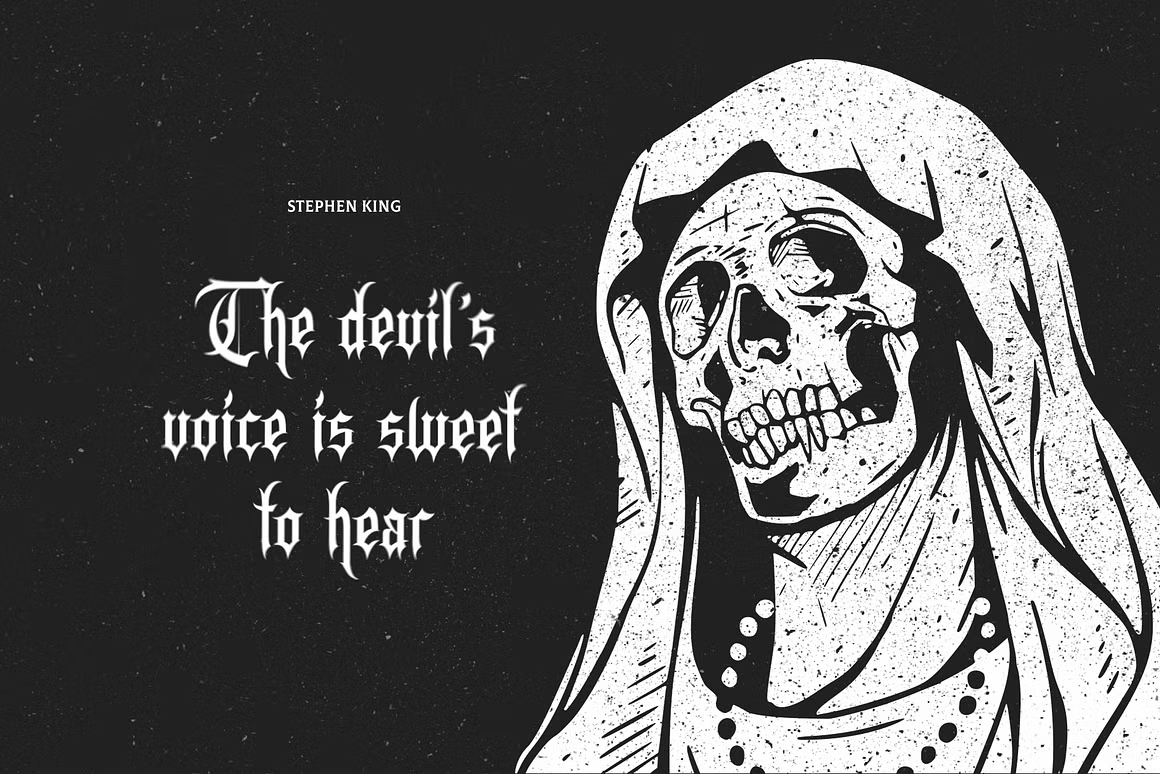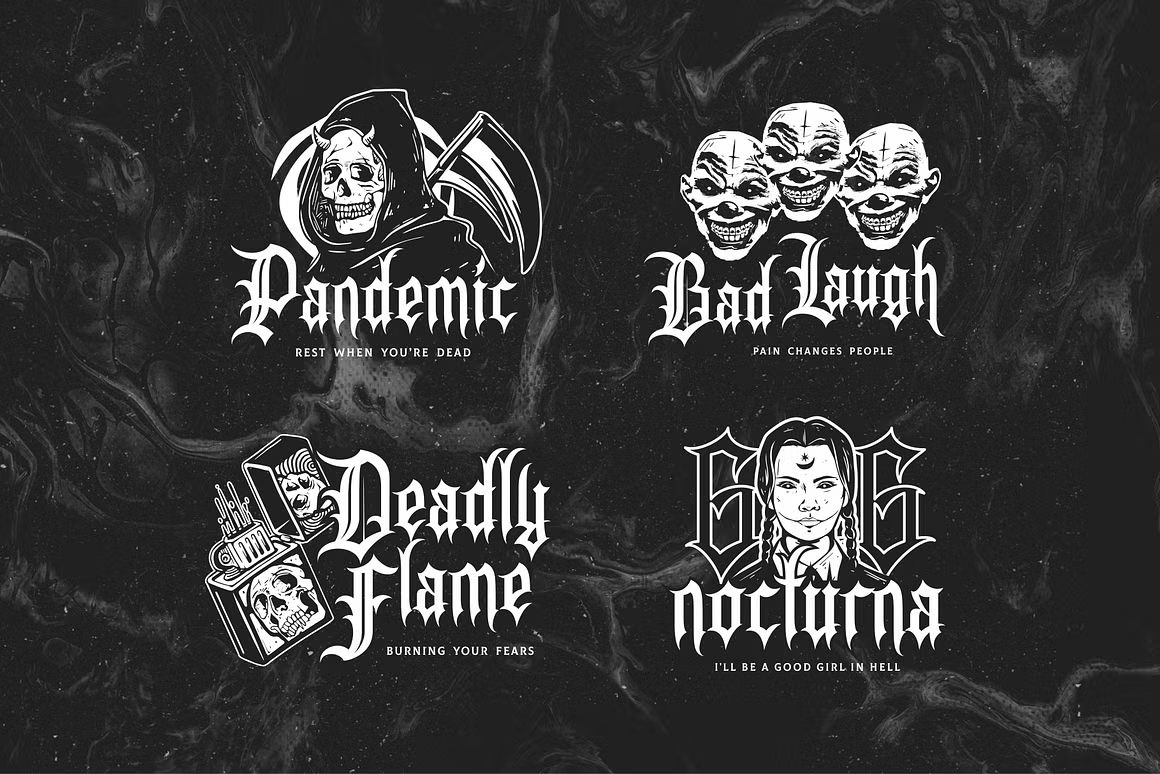
Anemouth Font
Description de Anemouth Font
Anemouth est une police Blackletter qui se mélange légèrement « plus sombre » et est quelque peu tangente à l’impression « diable ». Cette police est donc un corps classique avec une âme qui peut s’adapter au monde moderne.
Cette police conviendra aux noms/logos de groupes, aux couvertures d’albums, aux affiches de groupes de métal/hardcore/underground/punk, etc. En plus de cela, elle sera également idéale pour les marchandises telles que les t-shirts, les bandanas, les affiches de groupes, etc.
Nous donnons également une petite illustration bonus qui correspond au caractère effrayant de la police afin qu’elle vous aide à créer un excellent design.